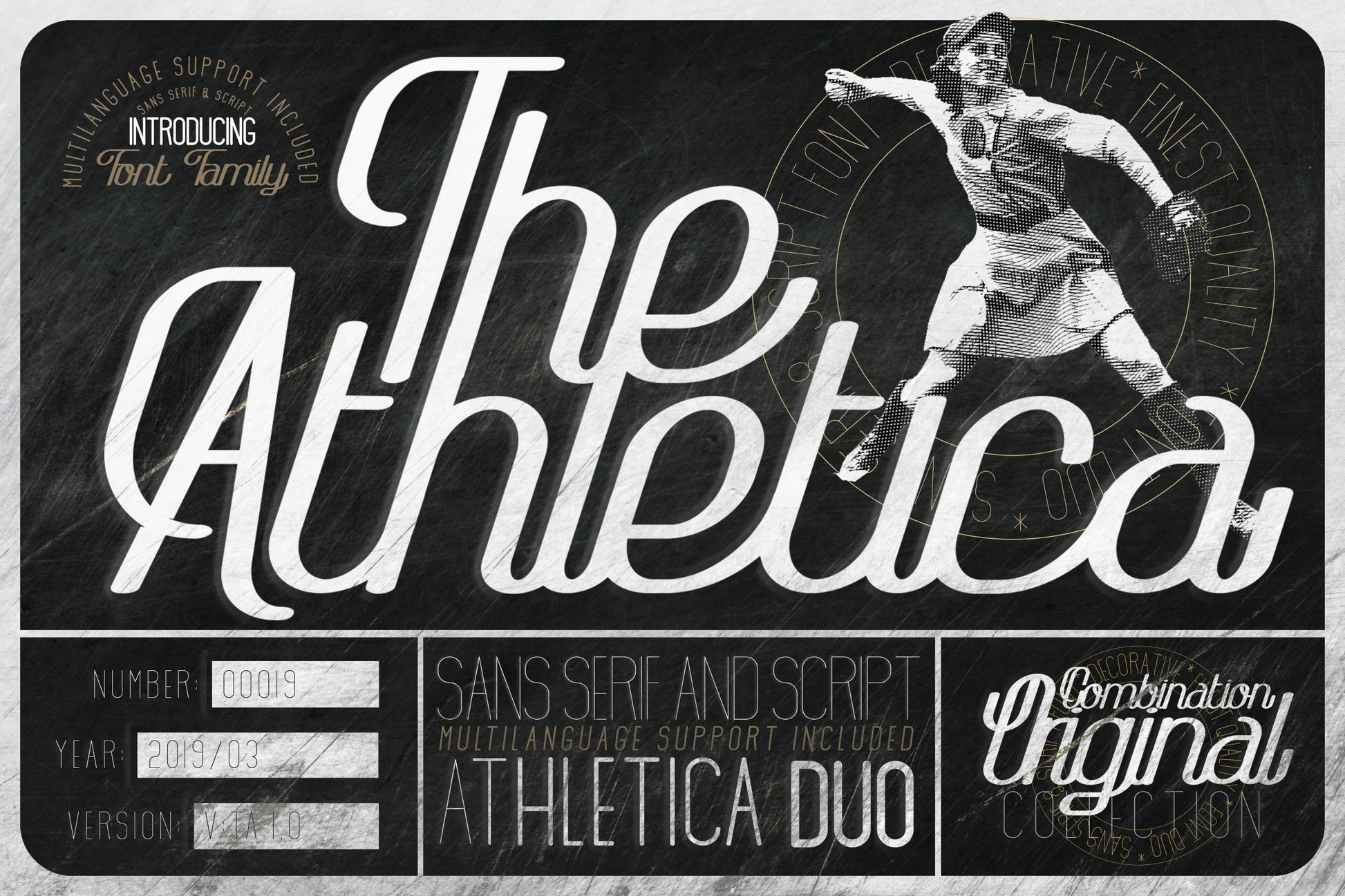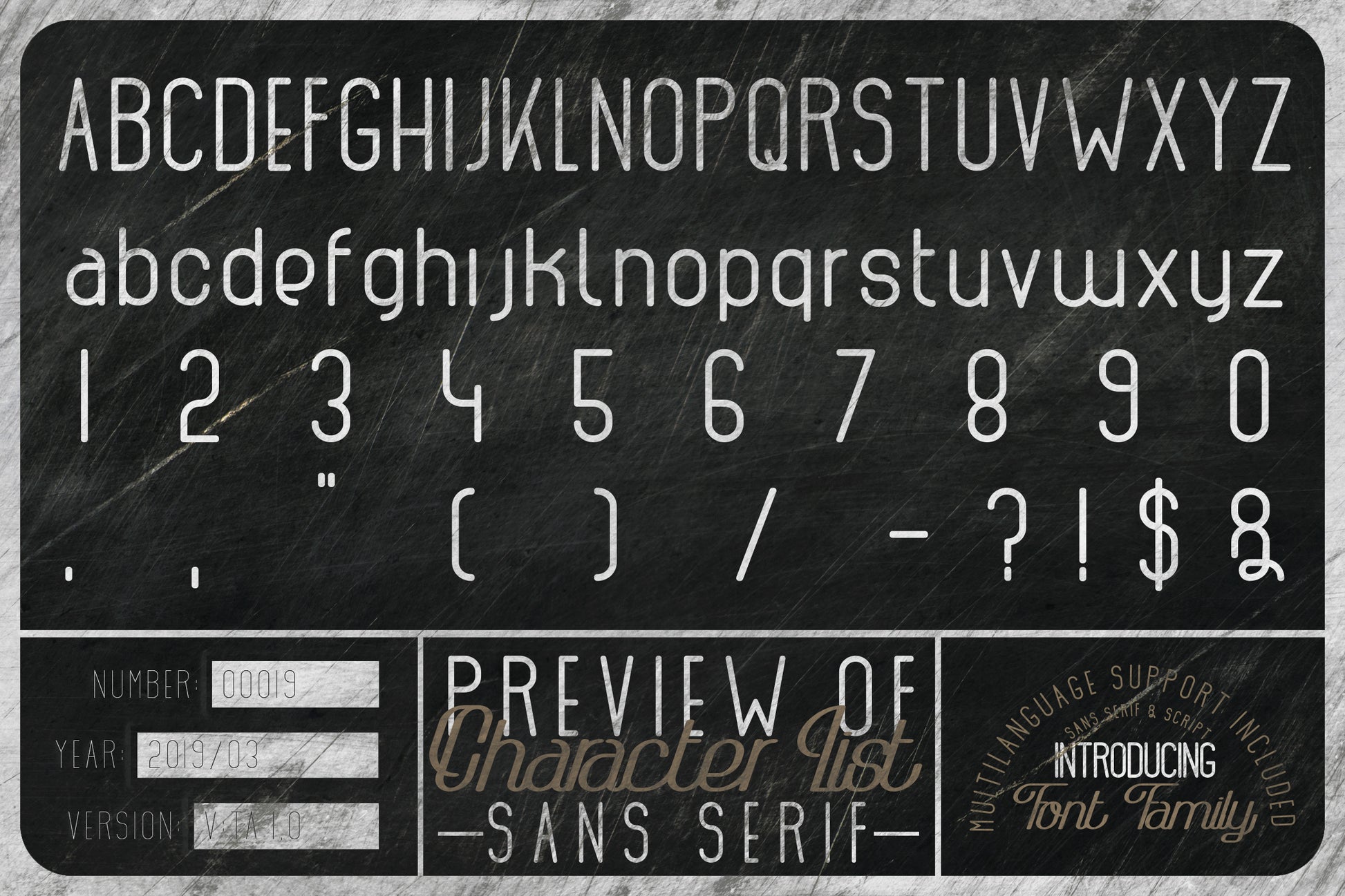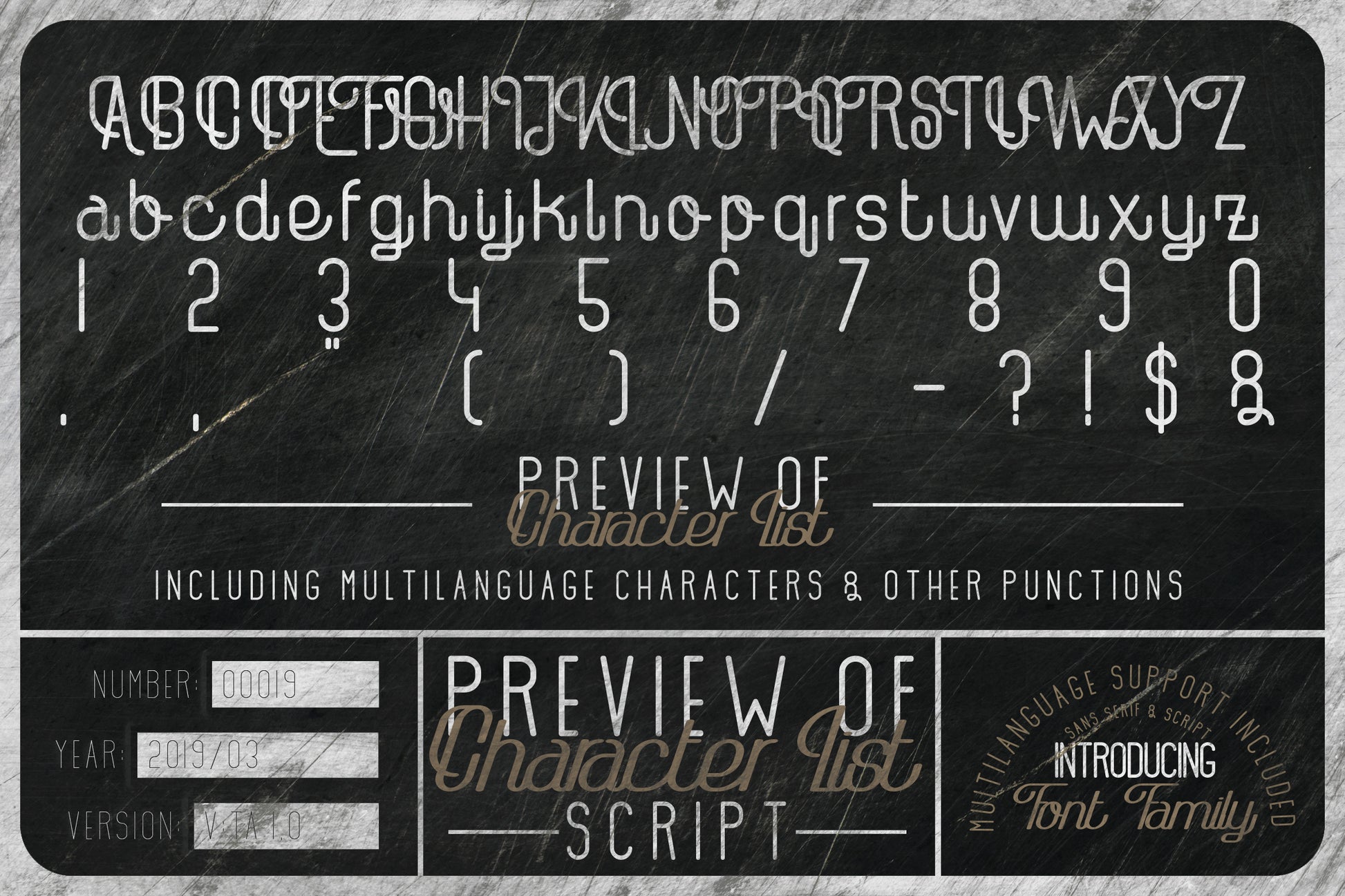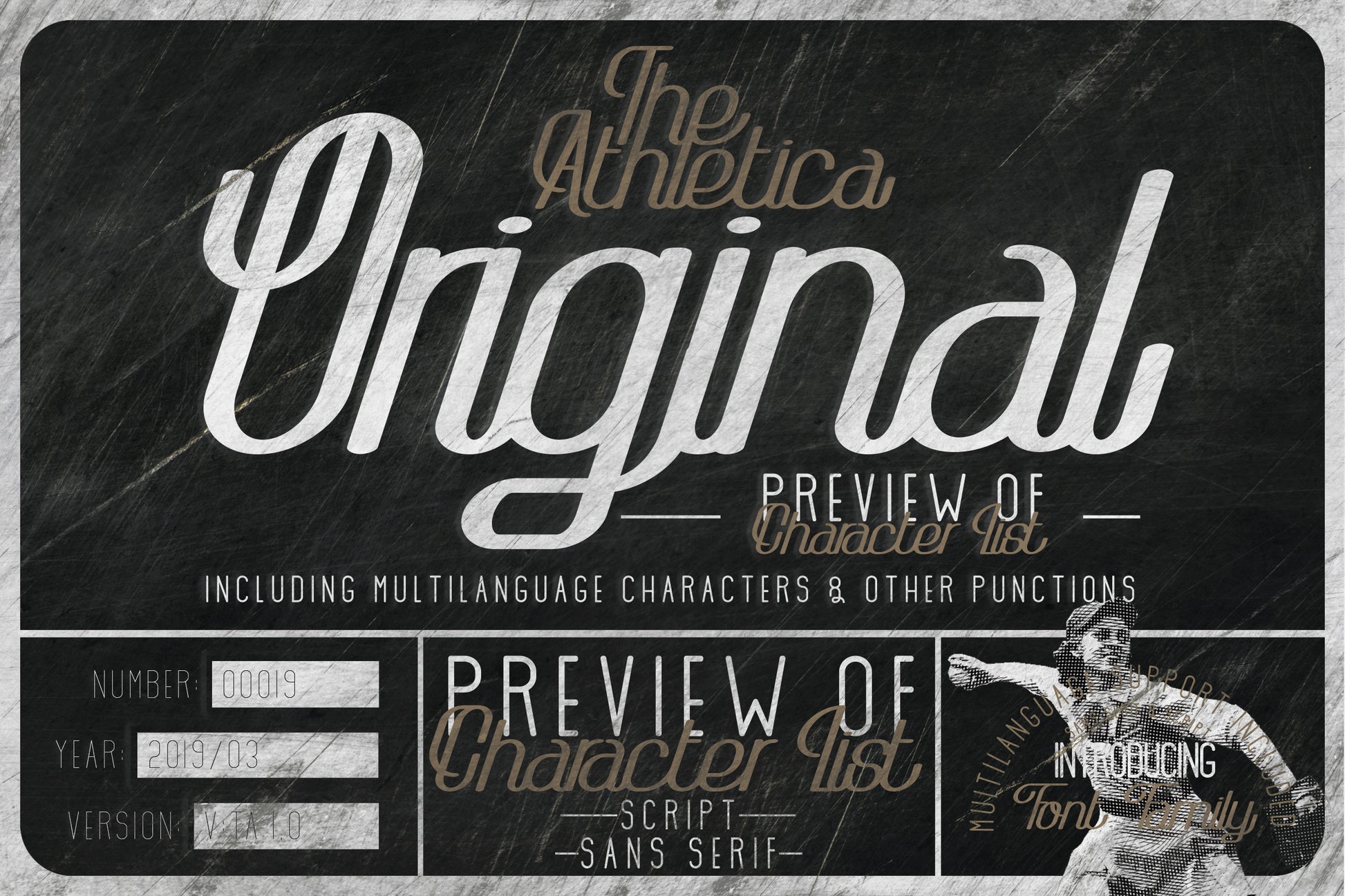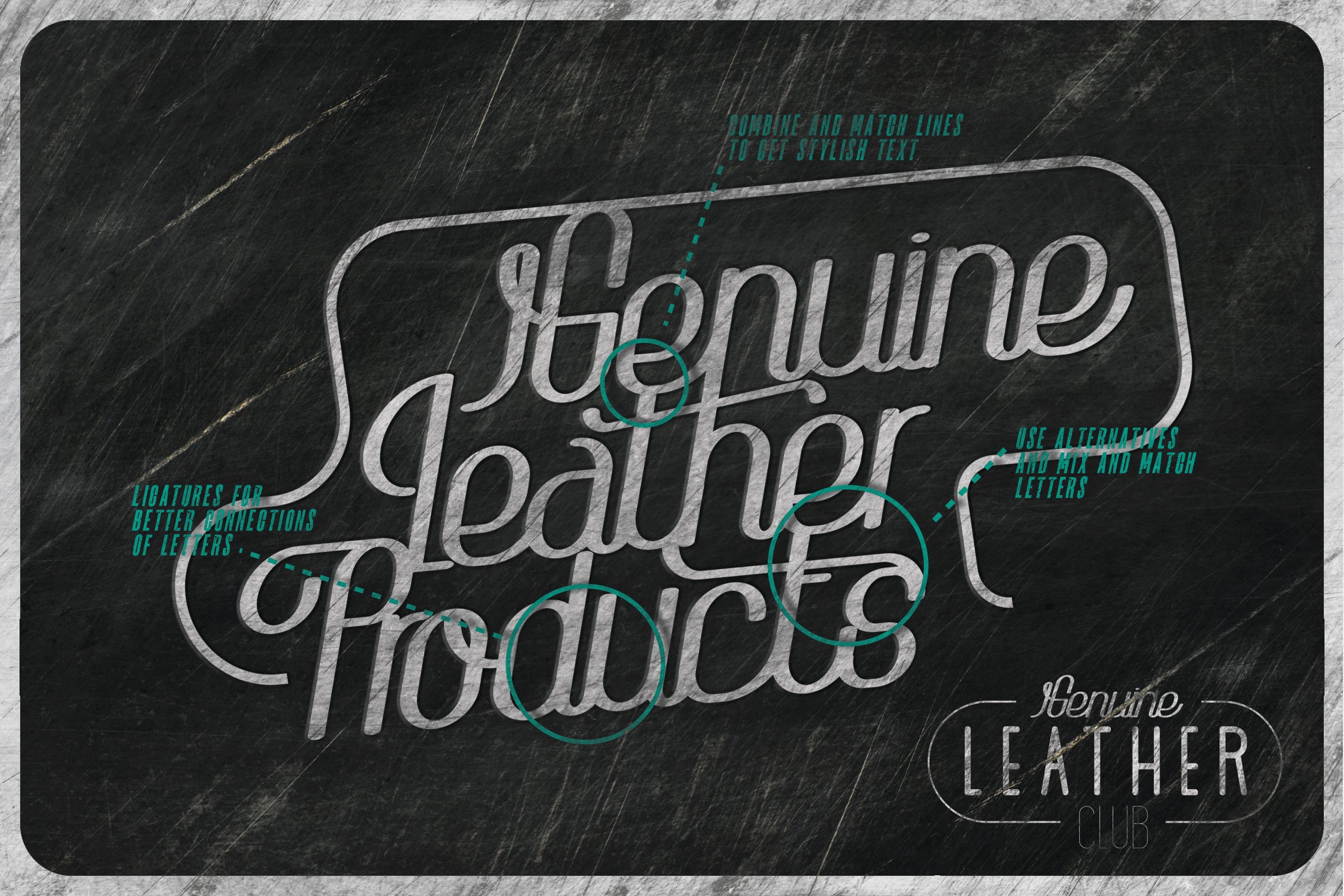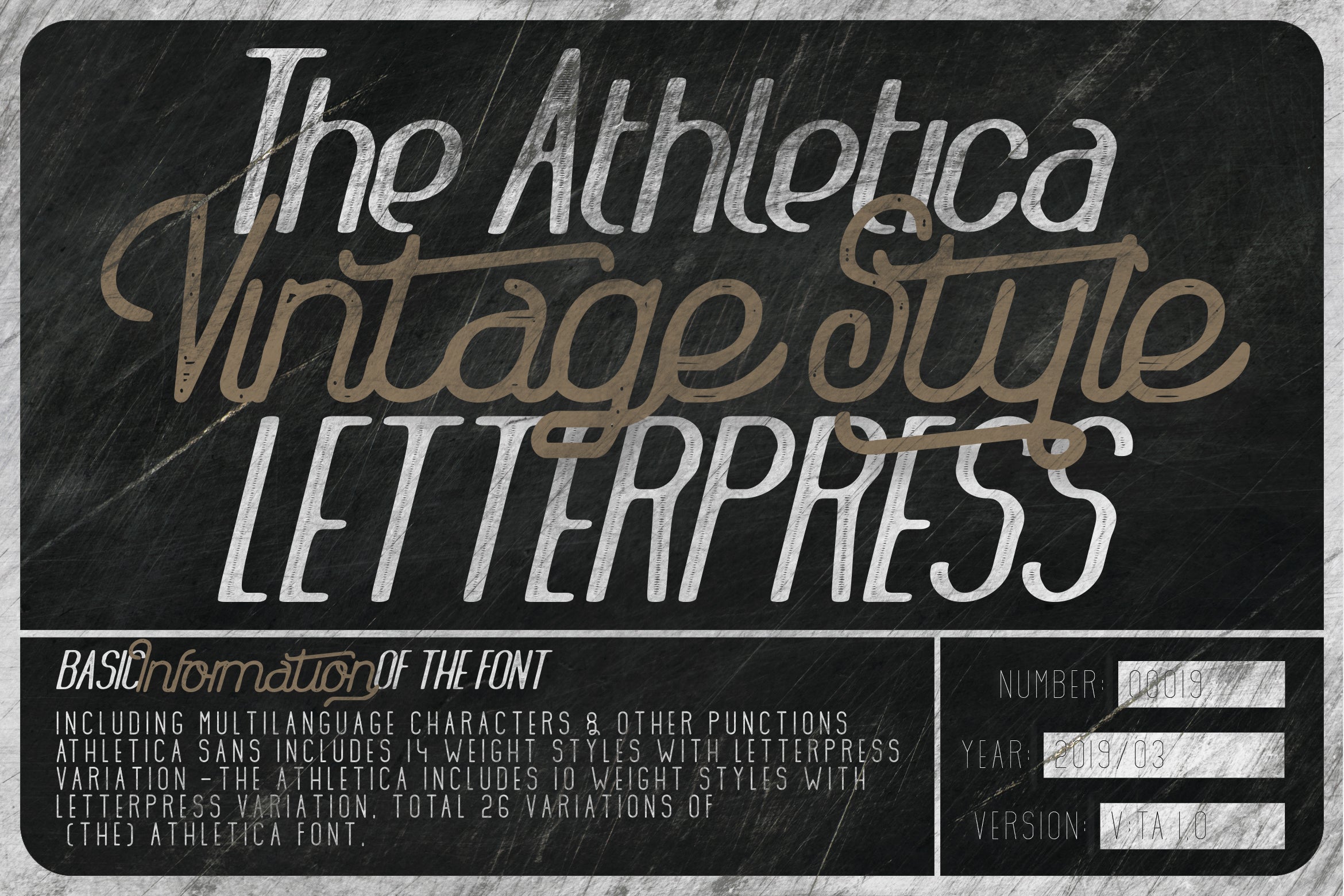
La fuente Athletica
La fuente Athletica es una fuente vintage monolineal y sans-serif, hecha a mano. Inspirada en carteles, revistas, postales y anuncios retro de los años 40 y 50.
La fuente viene con 26 estilos, desde Regular hasta Negro, variante Letterpress y muchos más.
La fuente permanece en la memoria una vez que la ves y es ideal para texto en pantalla, impresión y también para interfaces de usuario, dispositivos móviles, diseño web y carteles, con un conjunto de caracteres óptimos para tu diseño en cualquier diseño.
Se ve especialmente bien en gran escala, aunque todavía lo lleva en tamaños de punto más pequeños.
Características del Athletica:
Alternativas estilísticas y florituras
Ligaduras
Caracteres internacionales (multilingües)
Puntuación y símbolos
Características de OpenType
Características de Athletica Sans:
Mayúsculas y minúsculas
Caracteres internacionales (multilingües)
Puntuación y símbolos